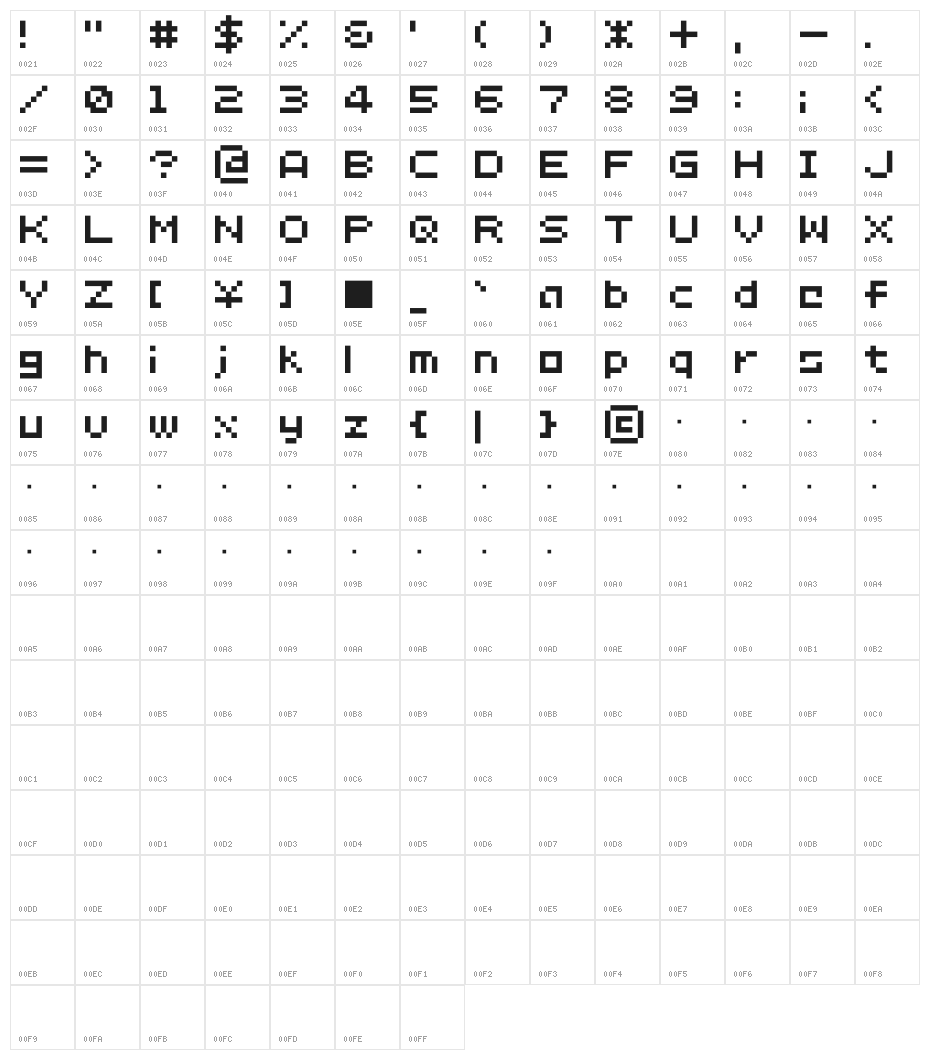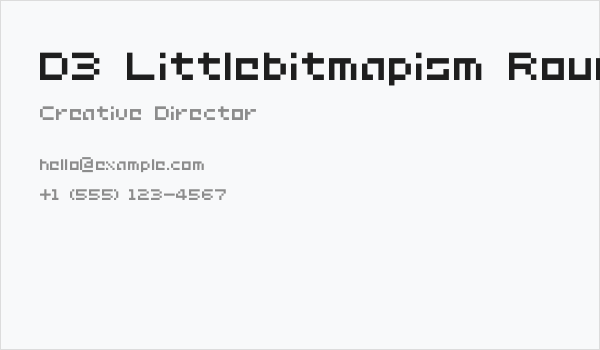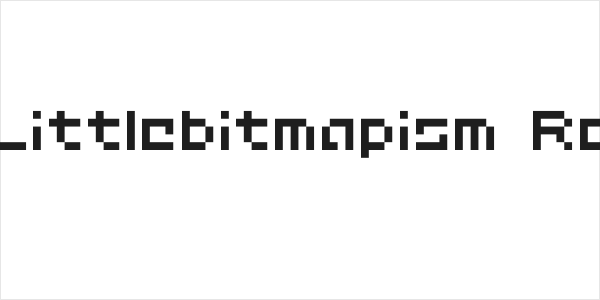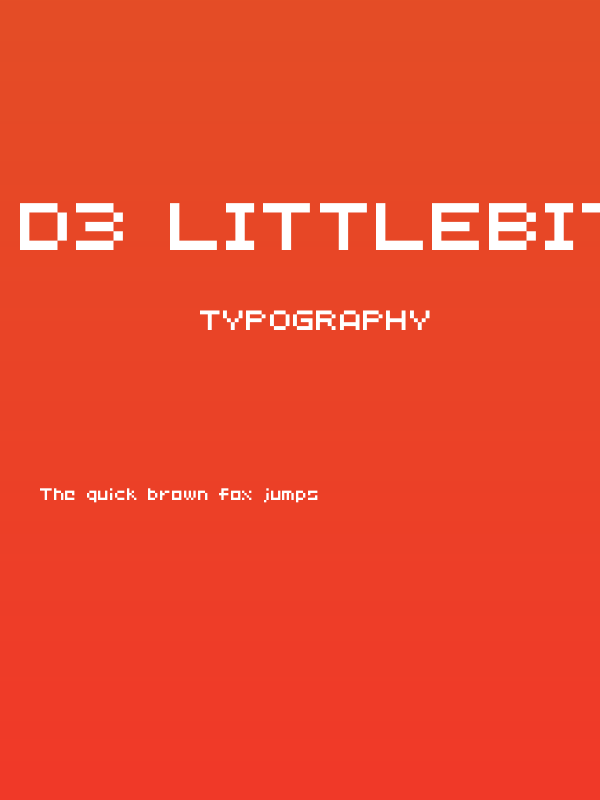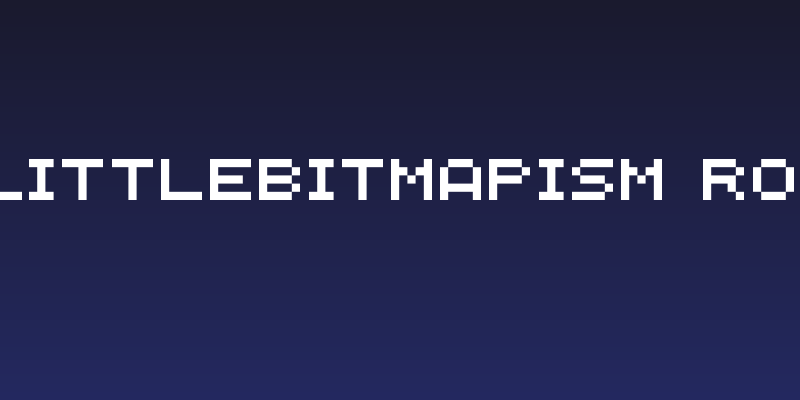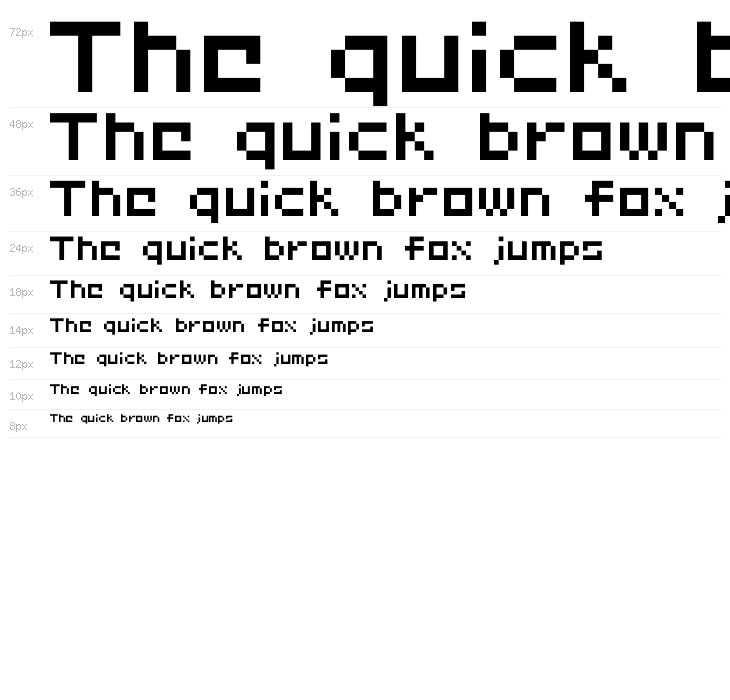
D3 Littlebitmapism Round Font
✎ Pixel
| Caso d'uso | Logos, Headlines, Digital Art |
| Progetti proposti | Ideal for retro video game designs, digital art projects, and nostalgic branding. |